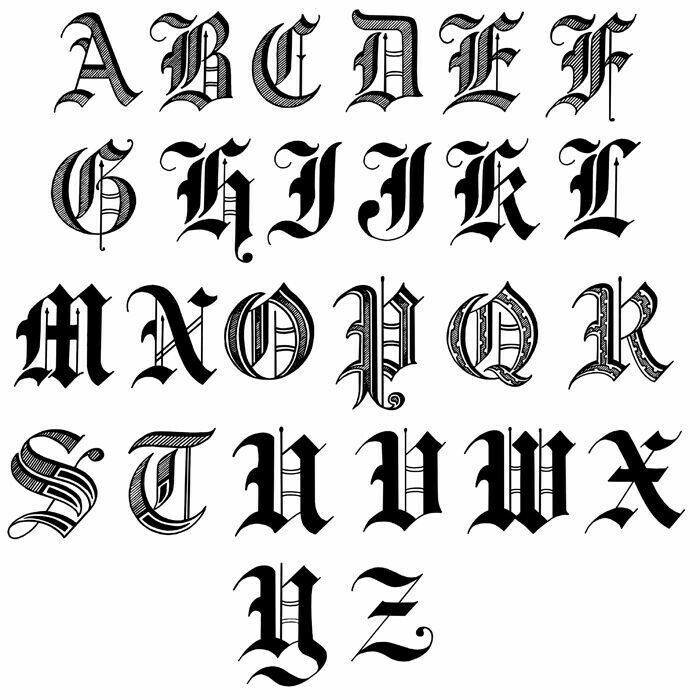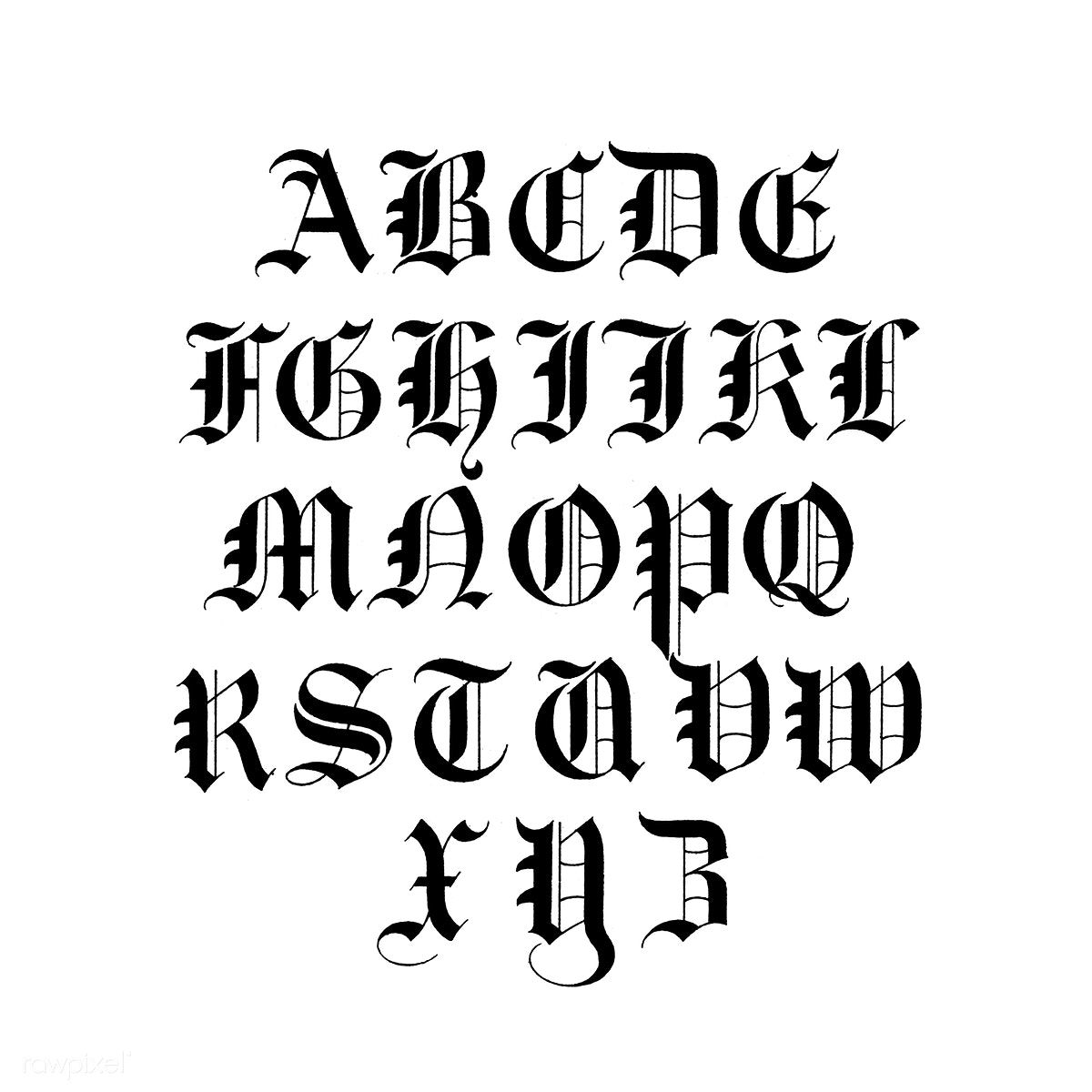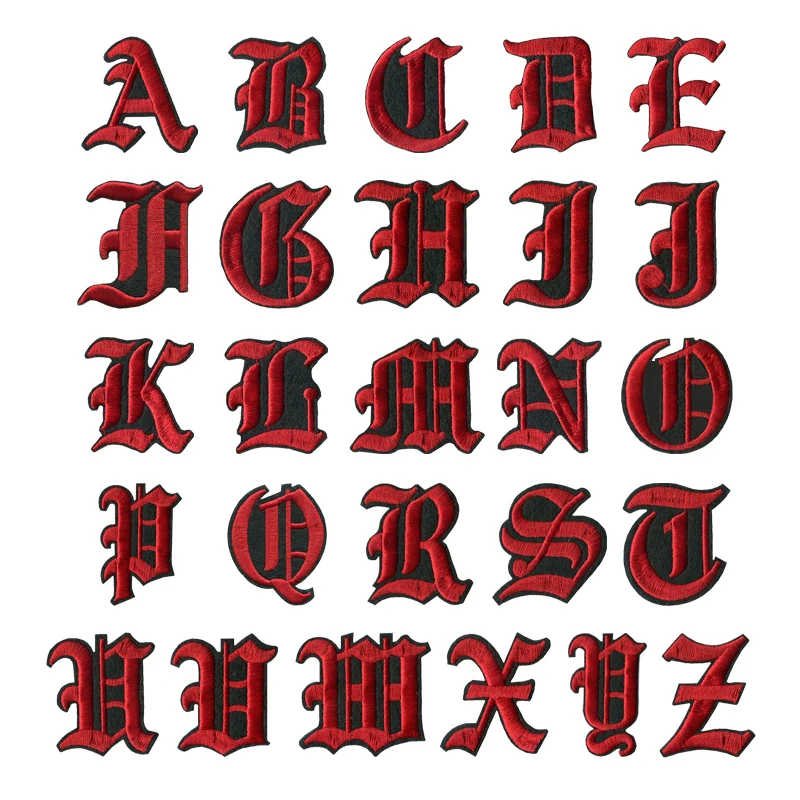
История готических шрифтов | artlab.
Заинтересовавшись историей шрифтов я постоянно нахожу что-то полезное и интересное, чем и стараюсь поделиться. Сегодня речь пойдет о готических, очень узнаваемых, шрифтах (многие именно с них начинают обучение каллиграфии).
Интересно, что готический стиль написания берет свое начало из греческого алфавита. В 300 г. до н.э. Александр Великий (Македонский) устанавливает греческий язык в качестве единого на огромной территории. Следующая Великая Империя – Римская, переняла удобную греческую письменность, но основным средством общения у римлян стал латинский язык с его прямым антиквенным шрифтом (здесь впервые появились засечки на заглавных буквах (капителях) – serifs). Латынь была заимствована у этрусков, буквы которых, в свою очередь, основывались на греческом алфавите.
В 395 г. н. э. в конце правления императора Константина, Римскую Империю наводнили германские варвары, уже имевшие к тому времени свой рунический алфавит, который называют также
футарком (futhark). Вот образец рунического алфавита готских (германских) тевтонов.
Благодаря распространению христианства в этот момент появляется необходимость в книгах и появляются тысячи монахов переписчиков, которые постепенно модифицировали написание шрифта и создавали новые стили.
Ниже приведен пример кельтского письма, называемого унциальным (scriptura uncialis), потому, что литеры записывались на четырёх направляющих линиях, отстоящих друг от друга на расстоянии одной унции (24,5 мм). Кельты сделали римское написание букв мягче и выразительнее
Дальнейшее развитие унциального письма привело к появлению четырёх форм: ирландское письмо (Ирландия и Англия), меровингское (Франция), Это письмо характерно появлением маленьких (то, что мы теперь называем “строчными”) букв. К концу 1000 г. н. э. из каролингского развилось романское письмо (Romanesque), которое к 1200 г. приобрело уже почти готический вид. Он и теперь известен под именем Black Letter, или, чаще, — старо-английское письмо (Old English).
Ранний готический шрифт (протоготический) – был широко распространен в западной Европе и использовался со второй половины 11 века до середины 13 века, в период между концом каролингской эпохи и началом готической. Поэтому может рассматриваться как переход от каролингского минускула к текстуре, т.к. сочетает в себе элементы этих написаний.